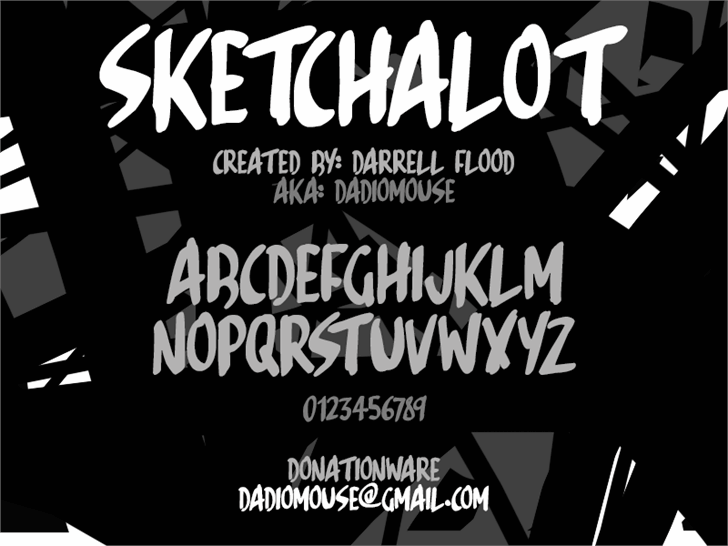
Sketchalot Font – Download Grátis
A Sketchalot Font é uma elegante e versátil fonte script criada pelo designer Darrell Flood. Com seus traços fluidos e detalhes sofisticados, ela se destaca como a escolha perfeita para projetos pessoais e casuais. Oferecida gratuitamente para uso personalizado, essa fonte traz uma graça única aos textos que você escrever. Independente de ser um designer gráfico iniciante ou experiente, a Sketchalot Font é o complemento perfeito para suas tarefas diários. E mesmo se você estiver disposto a apoiar os criadores com uma doação, sabemos que ela não precisaria de nada além dos elogios e aplausos da comunidade. Darrell Flood está sempre buscando inovar e fazer novas fontes, todas voltadas para o uso pessoal. A Sketchalot Font é mais um exemplo disso. Com apenas alguns cliques, transforme a forma como escreve ou cria designs digitais. Sua versão gratuita oferece uma ampla gama de caracteres, garantindo que você possa personalizar seus projetos de maneira única e imprimível.
Designer: Darrell Flood